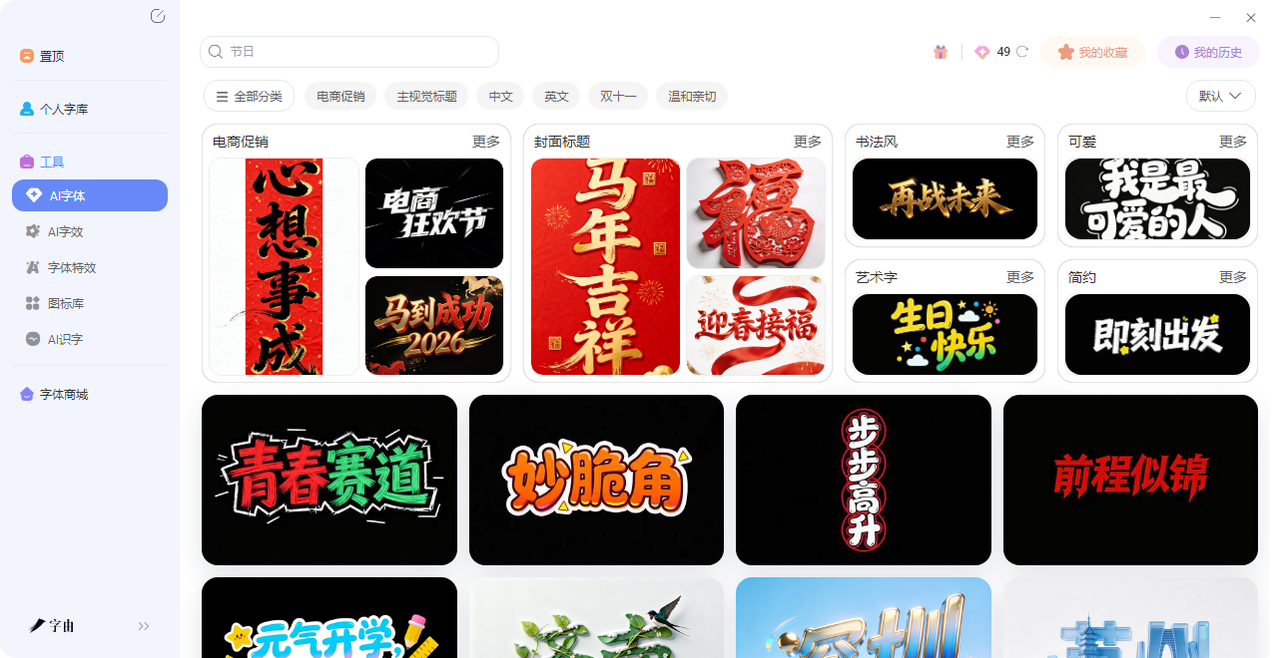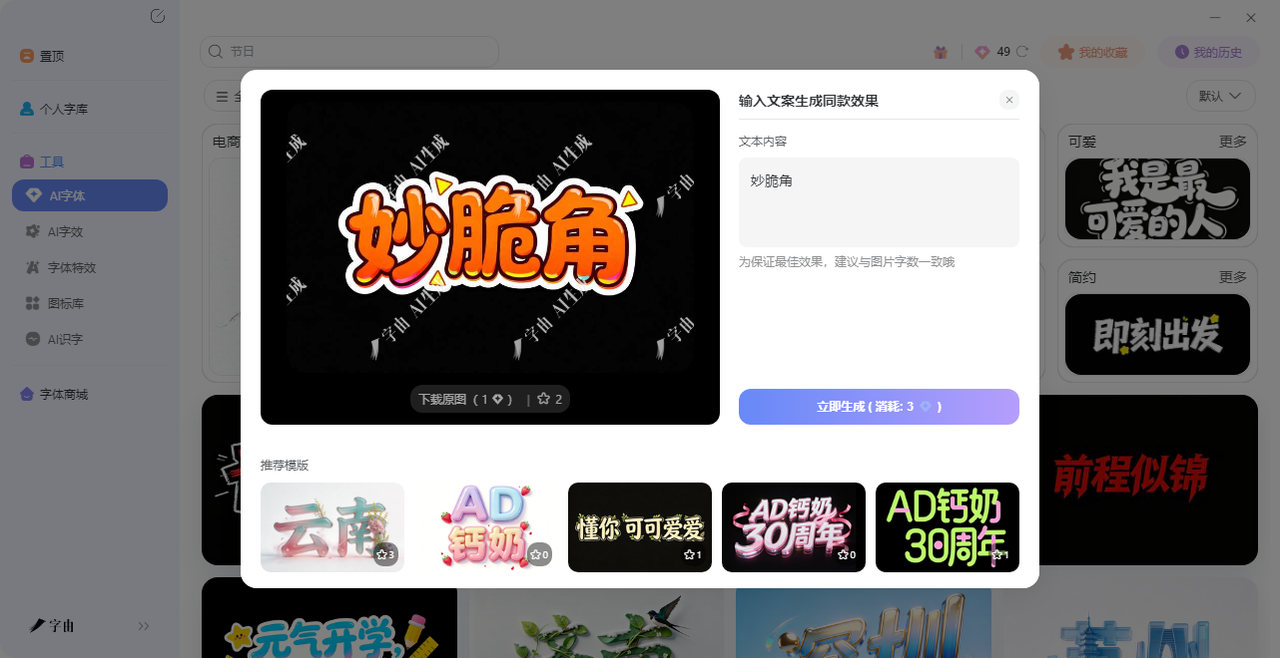
上次做一张音乐节海报,花了两天找参考,半天调构图,结果卡在标题字上。想做个霓虹灯管效果,在PS里调了半小时图层样式,光影不对,颜色失真。后来同事甩过来一个链接,说“你试试这个”。输入文字,选了个“霓虹”模板,点一下,几十秒就出图了。那时候才意识到:做艺术字这件事,根本不用自己动手调。下面这5 个免费艺术字生成工具是我自己摸索出来的感觉非常好用的,每个都能让你输入文字就拿到能用的艺术字。需要的直接收藏,以后做海报、封面、Logo再也不用为标题字发愁。
字由的“AI字体”功能,是我用过最顺手的免费艺术字生成工具。它把霓虹、金属、国潮、水彩这些效果做成了模板,你不需要会设计,也不需要懂参数,输入文字,选个模板,点一下,几十秒就能拿到一张带特效的艺术字。接下来我会教大家详细的步骤并附带说明:
第一步:打开字由客户端或网页版,进入【AI字体】页面。在搜索框里输入你想要的效果,比如“霓虹”“金属”“国潮”“手写”“3D”,系统会筛出对应的模板。想找复古霓虹风,搜“霓虹”;想要金属质感,搜“金属”;想做国潮海报,搜“国潮”。每个模板都有预览图,鼠标滑过就能看到用你的文字实时展示的效果。
第二步:选一个顺眼的模板,点击“做同款”,把模板里的文字换成你的标题(最好和模板字数一样)。点击“立即生成”,等20-30秒,就能拿到一张高清艺术字图片。生成后可以预览效果,不满意就换其他模板再试。每天有免费算力点,日常试用完全够用。
第三步:下载时有两个选项:带背景的可以直接用,透明背景的更方便后期排版。直接保存PNG格式,就能拖进PS、Canva、剪映里用。不需要抠图,不需要调色,模板里都给你做好了。如果你用的是PS、AI、Figma这些软件,字由的客户端还能一键应用字体——选中文字图层,在字由点一下,文字实时切换,不用下载安装包,不用重启软件。
如果是我的话,我会推荐以下几款艺术字效果:
- 霓虹灯管:带玻璃管质感的霓虹字,适合音乐海报、酒吧招牌、夜店活动
- 金属质感:拉丝不锈钢、铬金属高光、古铜做旧,适合科技产品、工业风设计
- 国潮书法:水墨晕染、毛笔飞白,适合国风海报、传统文化内容
- 水彩晕染:边缘模糊、颜料渗开的效果,适合文艺类封面、手账标题
- 3D立体:带厚度和透视的立体字,适合游戏标题、品牌Logo
- 节日喜庆:大红底色、金色描边、灯笼装饰,适合春节、促销活动
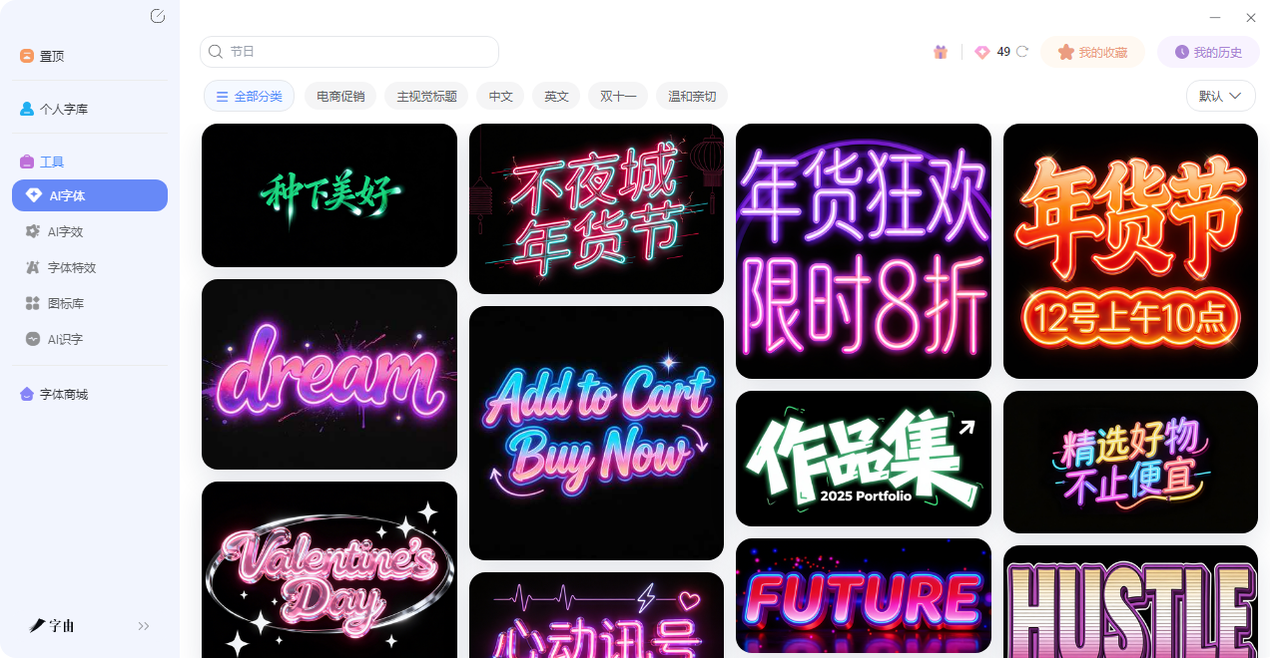
2、Text Fancy
Text Fancy 是一个专门生成ASCII艺术字的免费艺术字生成工具。输入文字,它会自动生成几十种由字符组成的艺术字。风格包括:Blocks in two lines - filled、Shady、Splash、Pipes、Acrobats、Blackie、1st Grade等。
这些艺术字由字母、数字、符号拼成,适合用在代码注释、论坛签名、终端界面、或者任何需要“复古感”的地方。生成后直接复制文本,不用下载图片。如果你喜欢那种早期互联网的像素风格,这里会很对胃口。“Splash”风格我很喜欢,文字像被水溅开一样,用在代码注释里特别有意思。“Shady”风格带阴影效果,做论坛签名很酷。
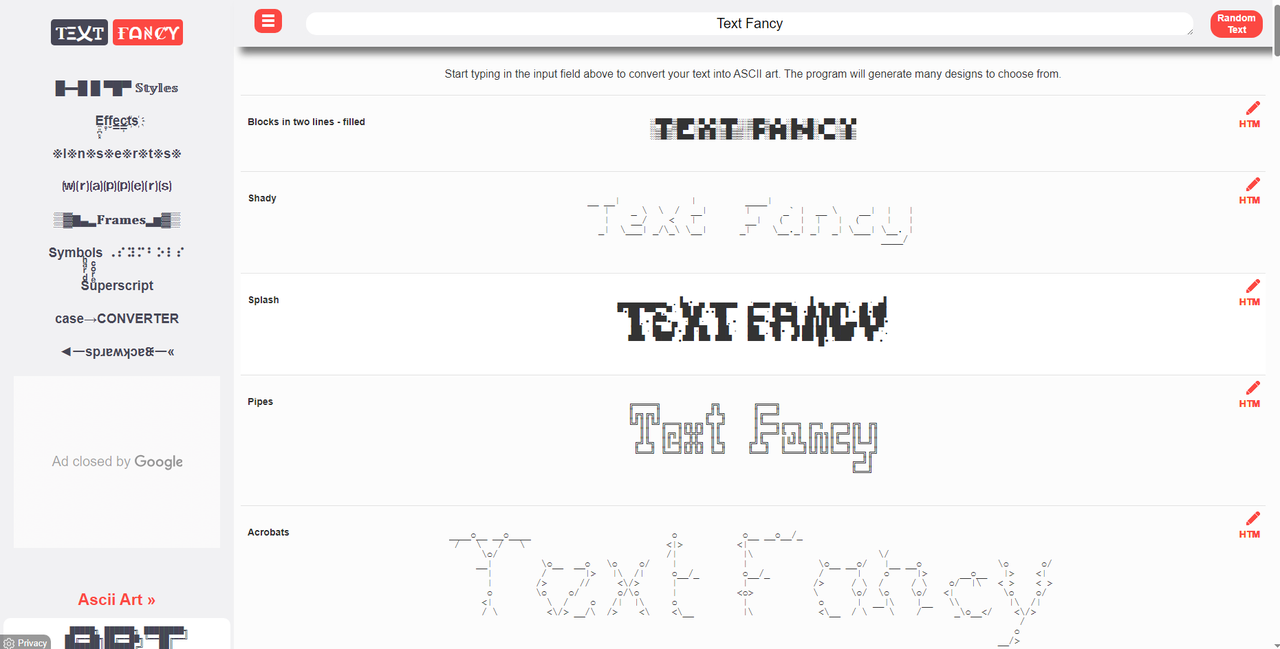
3、Font Meme
Font Meme 是一个老牌的文本图形生成器,提供几十种风格选项,操作很简单:输入文字,选一个风格,系统会生成对应的文本图形。比如选“Graffiti”,文字会变成涂鸦风格的图片;选“Tattoo”,会变成纹身风格。适合做Logo、海报标题、社交媒体封面。生成后可以直接下载图片。“Graffiti”风格做街头文化海报很对味,“Tattoo”风格做纹身参考图很合适。而且它家还支持上传自己的字体,生成个性化的效果。
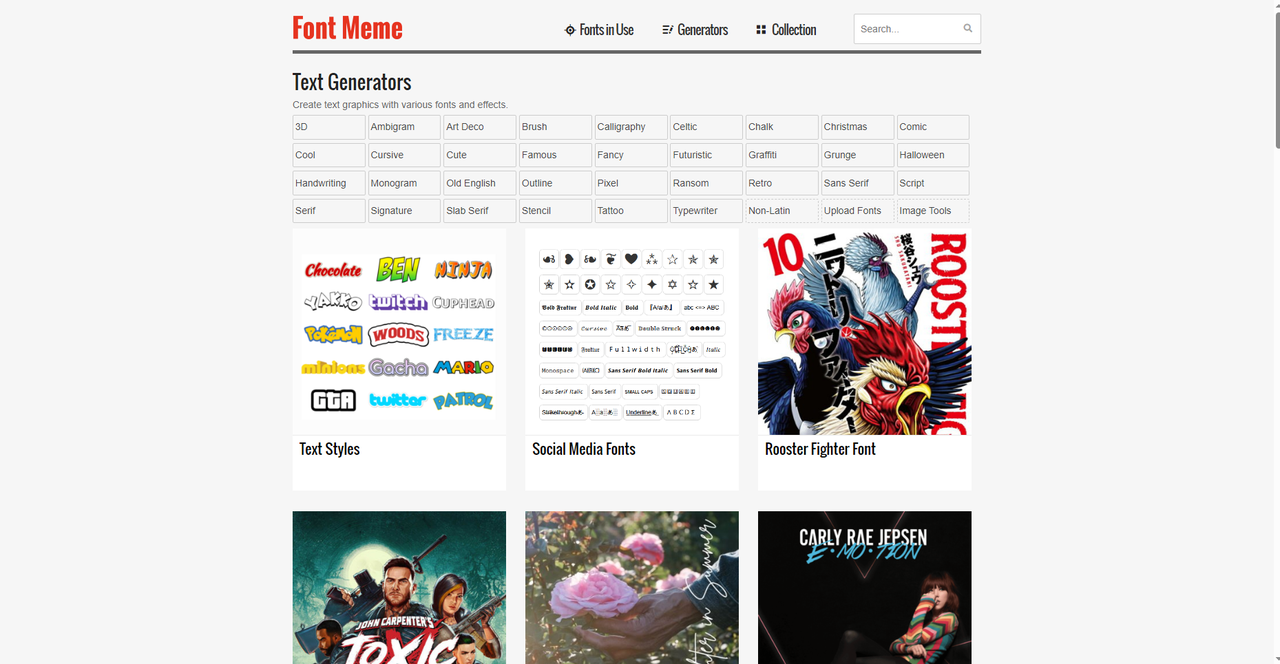
4、Fonts Generator
Fonts Generator 是一个专门生成花式字体的工具,生成的文字可以直接复制粘贴到社交媒体上。输入文字,下面会列出所有风格的预览,点“Copy”就能复制到剪贴板,直接去微信、微博、抖音、Instagram粘贴。完全免费,无需注册。适合喜欢在社交平台上想要获得高点击率的用户。“Cursive”风格做签名很优雅,“Bold”风格做标题很醒目。而且它家还支持调整字体大小,复制之前可以先调好。“Glitch”风格做故障艺术风文案很酷,“Symbol-Text”风格带符号装饰,发朋友圈的时候用,朋友都会多看一眼。
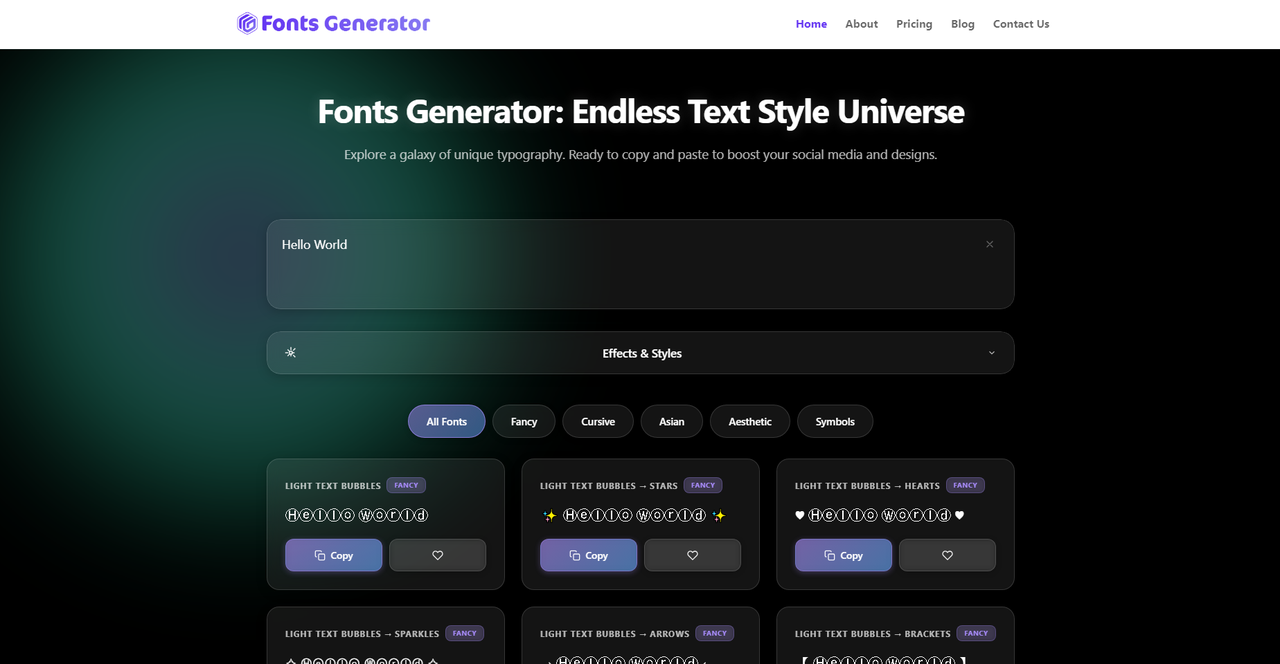
5、Text Art Font Generator
Text Art Font Generator 是一个专注于复古风格文本艺术字的免费艺术字生成工具,功能实用。输入文字后,可以选择多种字体样式,每种样式都会把普通文字转换成对应的Unicode字符。比如选“All Bubbles”,文字会变成带圆圈的气泡字体;选“All Parenthesis”,文字会带上括号装饰。适合做创意文案、社交媒体签名、或者任何需要“不一样”的文字效果。生成后直接复制即可。“All Bubbles”风格做朋友圈文案很可爱,“All Parenthesis”风格做评论区签名很个性。而且它家还支持“All SuperScript”,文字变成上标,用在化学式或者数学公式里很实用。“All FullWidth”风格把文字变成全角字符,在日文网站发帖很实用。“All MathBold”风格做数学公式里的粗体变量,看起来更专业。